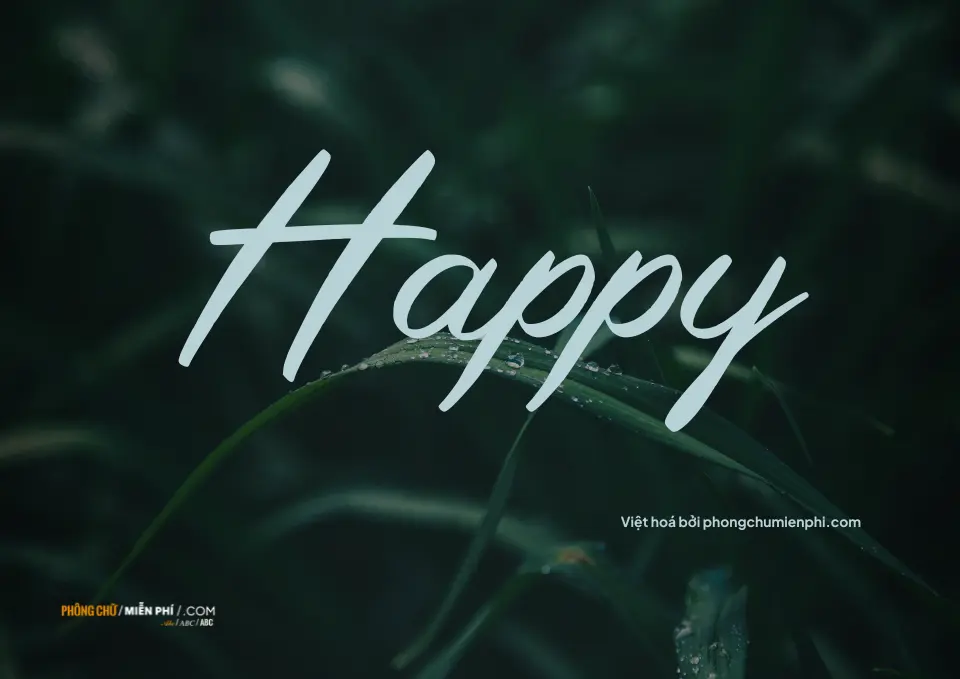
Tên font: Font Việt hoá Brushline
Font Việt hoá PCMP Brushline được việt hoá bởi phông chữ miễn phí.
PCMP Brushline là một phông chữ hiển thị đậm nét và có kết cấu, kết hợp những nét cọ nghệ thuật với phong cách hiện đại. Hoàn hảo cho các tiêu đề bắt mắt, thương hiệu sáng tạo, áp phích và tác phẩm nghệ thuật kỹ thuật số, phông chữ đa năng này mang đến cá tính và chiều sâu cho bất kỳ thiết kế nào. Với cảm giác thủ công và phong cách biểu cảm, Brushline là lựa chọn lý tưởng cho các nhà thiết kế đang tìm kiếm một diện mạo độc đáo và năng động. Tải xuống ngay để nâng tầm dự án của bạn với những nét vẽ đậm nét và phong cách nghệ thuật!